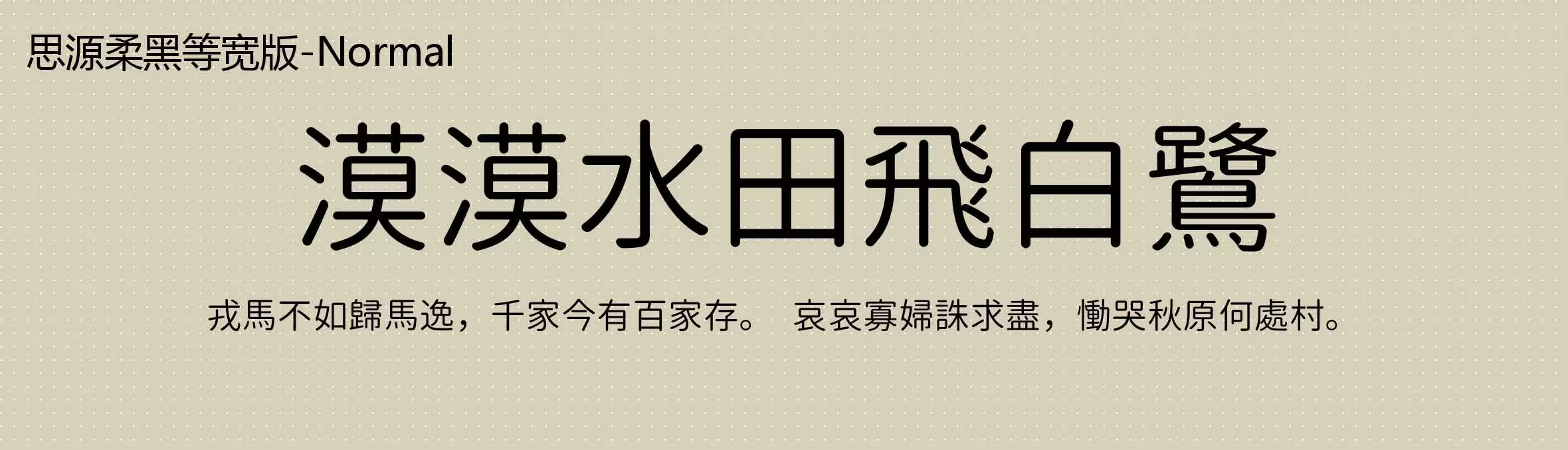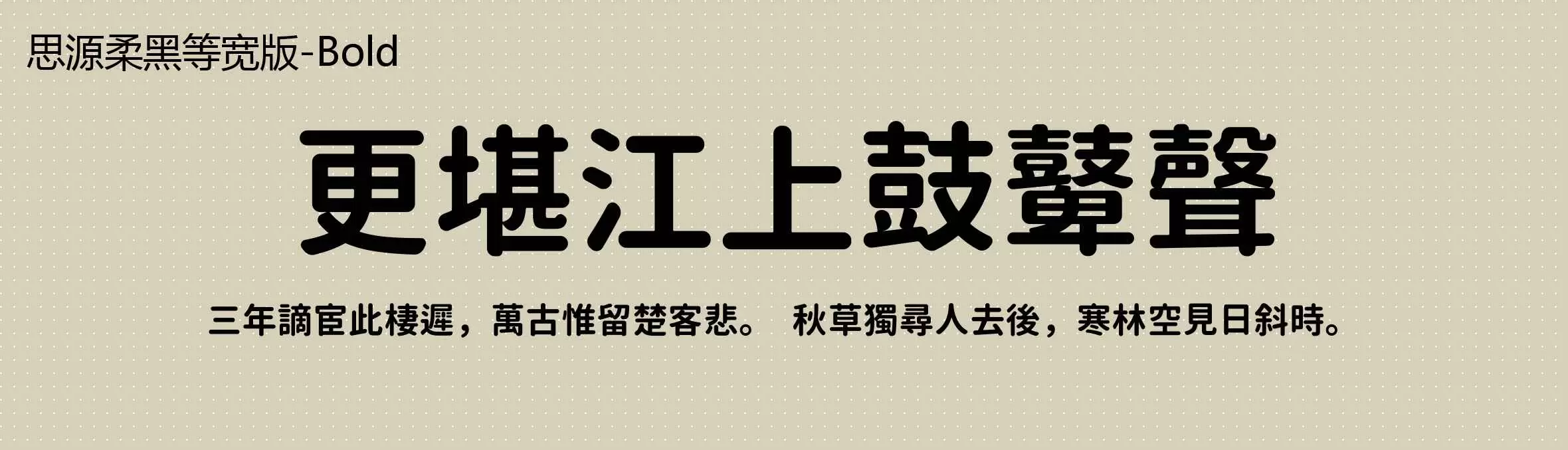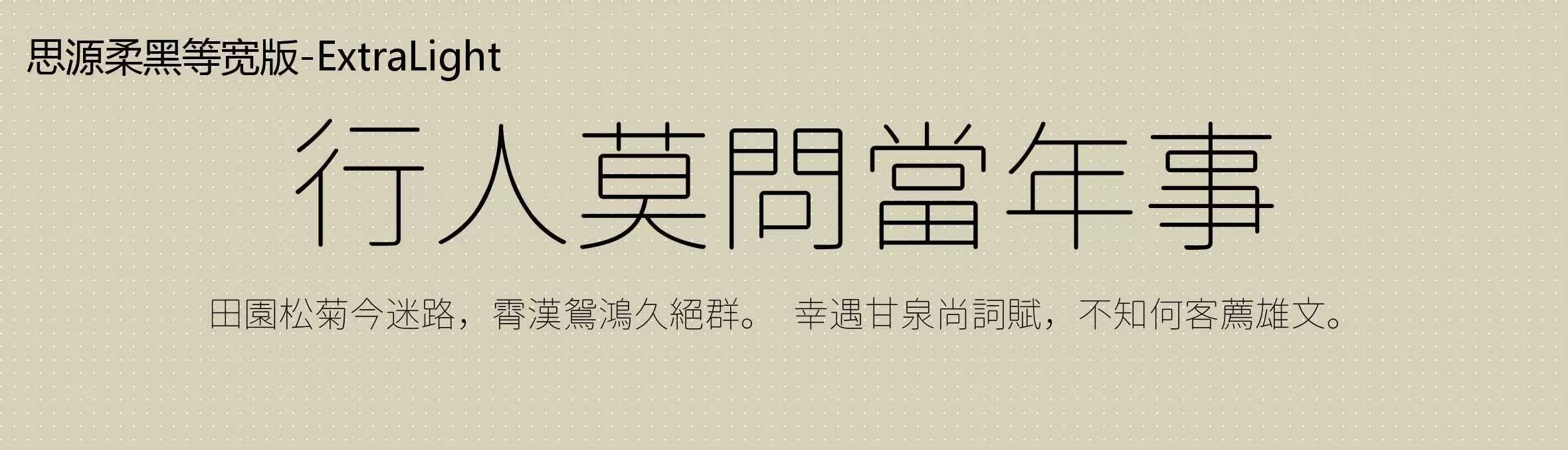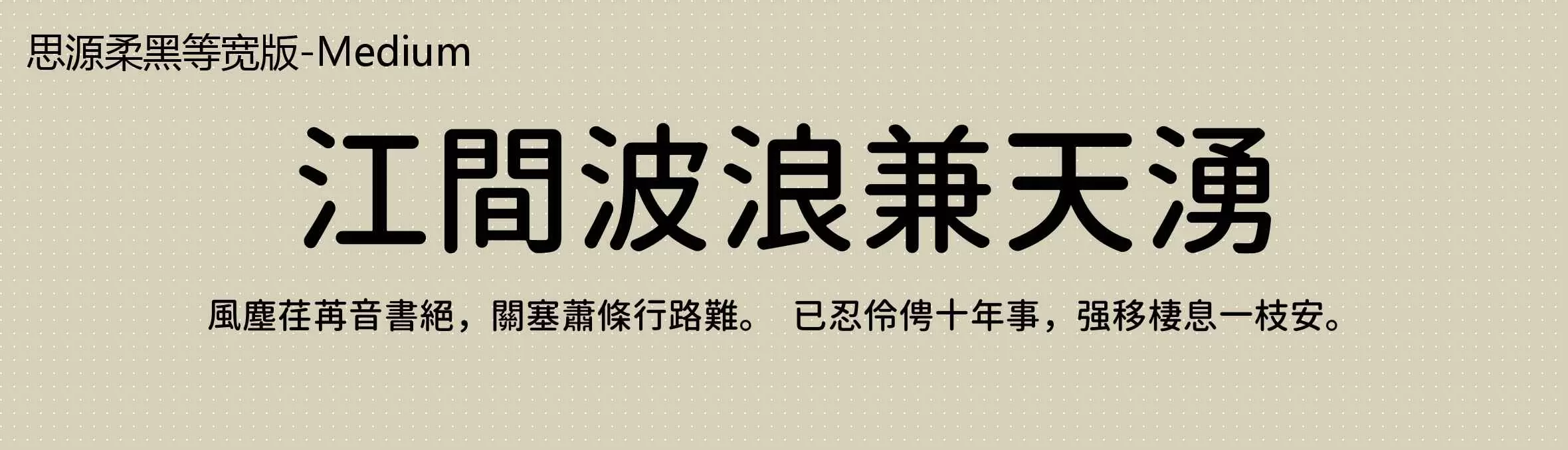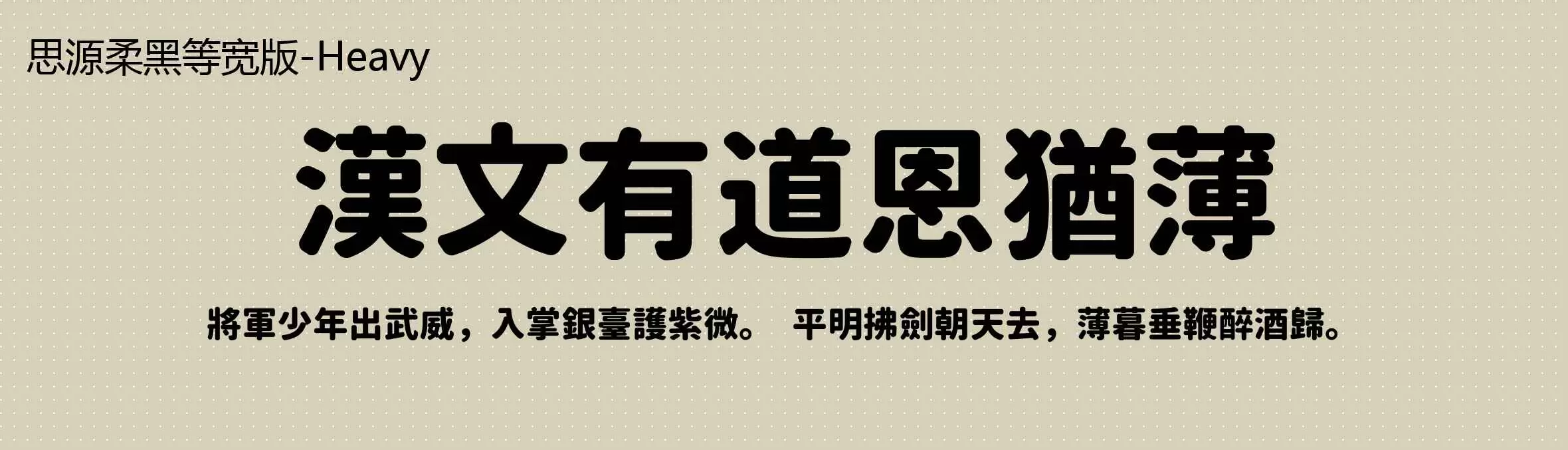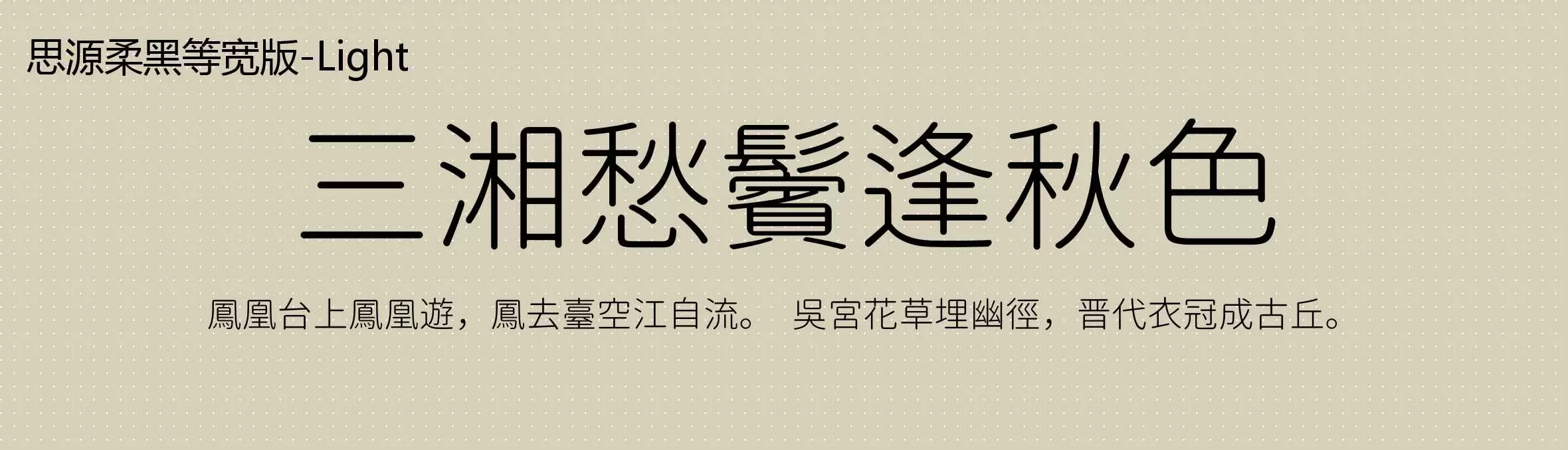
思源柔黑体(Gen Jyuu Gothic)是由日本自家製フォント工房 借由 Google 的开源字体「思源黑体」修改制作衍生而来,支持简体中文、繁体中文以及日文三种语言。字体开源并且无版权可免费用于商业用途,所以能应用的场景非常广泛。
「思源柔黑体」(源柔ゴシック) 与「圆体」比较相似,它继承了思源黑体的优雅设计以及可读性,并将文字的边角进行圆角化处理,使得整个字体看起来更加的可爱、年轻有活力。